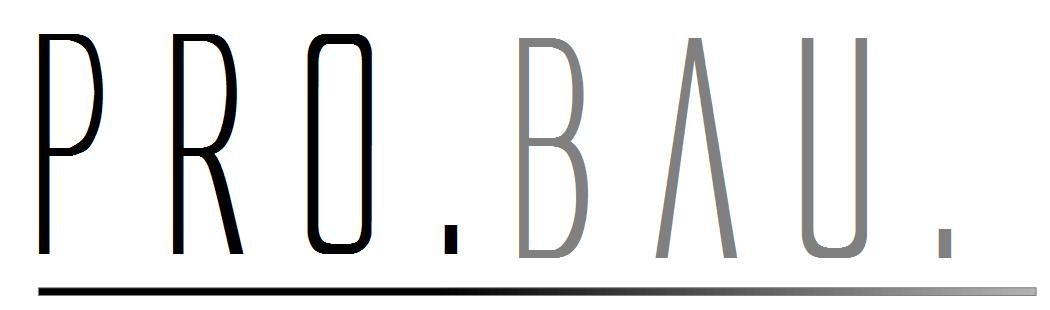
Wer kennt diese Schirft (Pro Bau)
Das ist ein Freefont namens "Alien League". Voller handwerklicher Unzulänglichkeiten und nicht schön anzuschauen …
Wenn die für das Logo einer Baufirma ausgewählt wurde, würde ich mir zumindest eine Versicherung gegen Baumängel zulegen, ließe ich mir von denen ein Haus bauen.